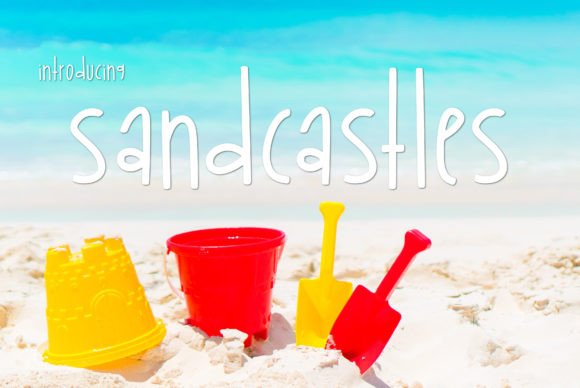
Sandcastles
適切なデザイン要素を見つけるのは難しい場合がありますが、Sandcastlesは作品を即座に引き立てる優れたコレクションを提供します。
POD(オンデマンド印刷)製品、結婚式の招待状、またはソーシャルメディアのグラフィックを作成している場合でも、Sandcastlesは理想的です。